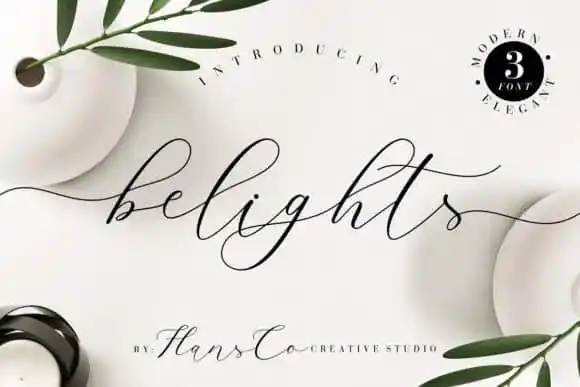
Belights Calligraphy Font
Belights Calligraphy Font é uma elegante tipografia à mão onde as linhas são suaves e naturais, oferecendo elementos vívidos e ligas únicas que tornam a experiência de escrita ainda mais gratificante. Seus detalhes perfeitos se destacam em diferentes tipos de projetos design, desde cartões de aniversário criativos até postagens de redes sociais atrativas e convites casamento sofisticados. Este font foi desenvolvido pelo site 99designs, onde designers do mundo inteiro apresentam suas criações para serem avaliadas por clientes interessados em adquirir seus trabalhos. A Belights Calligraphy Font é perfeita para qualquer designer que busca um toque único e criativo para seus projetos visuais, proporcionando uma experiência de escrita única e profissional que certamente irá deixar sua marca.